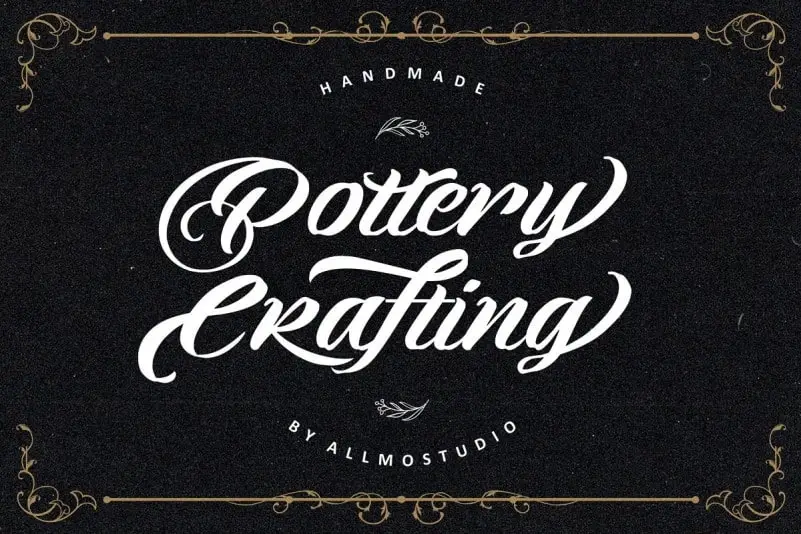
Pottery Crafting Script Font – Fonte Grátis
Pottery Crafting Script Font
A introdução da fonte “Pottery Crafting Script Font” é uma exibição encantadora e casual de escrita gótica, fornecendo ao designer um estilo agradável e natural. Este script vem como uma opção perfeita tanto para tatuagens ou posts em redes sociais quanto para projetos de DIY com o objetivo de transformar ideias criativas em obras de arte verdadeiras! Ele é perfeito para logotipos, cabeçalhos, camisetas e embalagens, entre outras aplicações onde você precisa de um estilo gótico e legível. O “Pottery Crafting” vem com maiúsculas e minúsculas, números, pontuação e uma infinidade de variações em cada caractere, incluindo alternativas OpenType e Ligaturas. Suporta o conjunto de caracteres para múltiplas línguas europeias orientais, garantindo que você tenha um estilo elegante em qualquer projeto. Com a fonte “Pottery Crafting Script Font”, designers e criadores podem experimentar novos desafios e expressões com uma variedade incrível de opções. Que tal transformar sua próxima obra de arte digital em algo ainda mais especial, utilizando essa fonte que é tanto um complemento como uma ferramenta para seu trabalho?